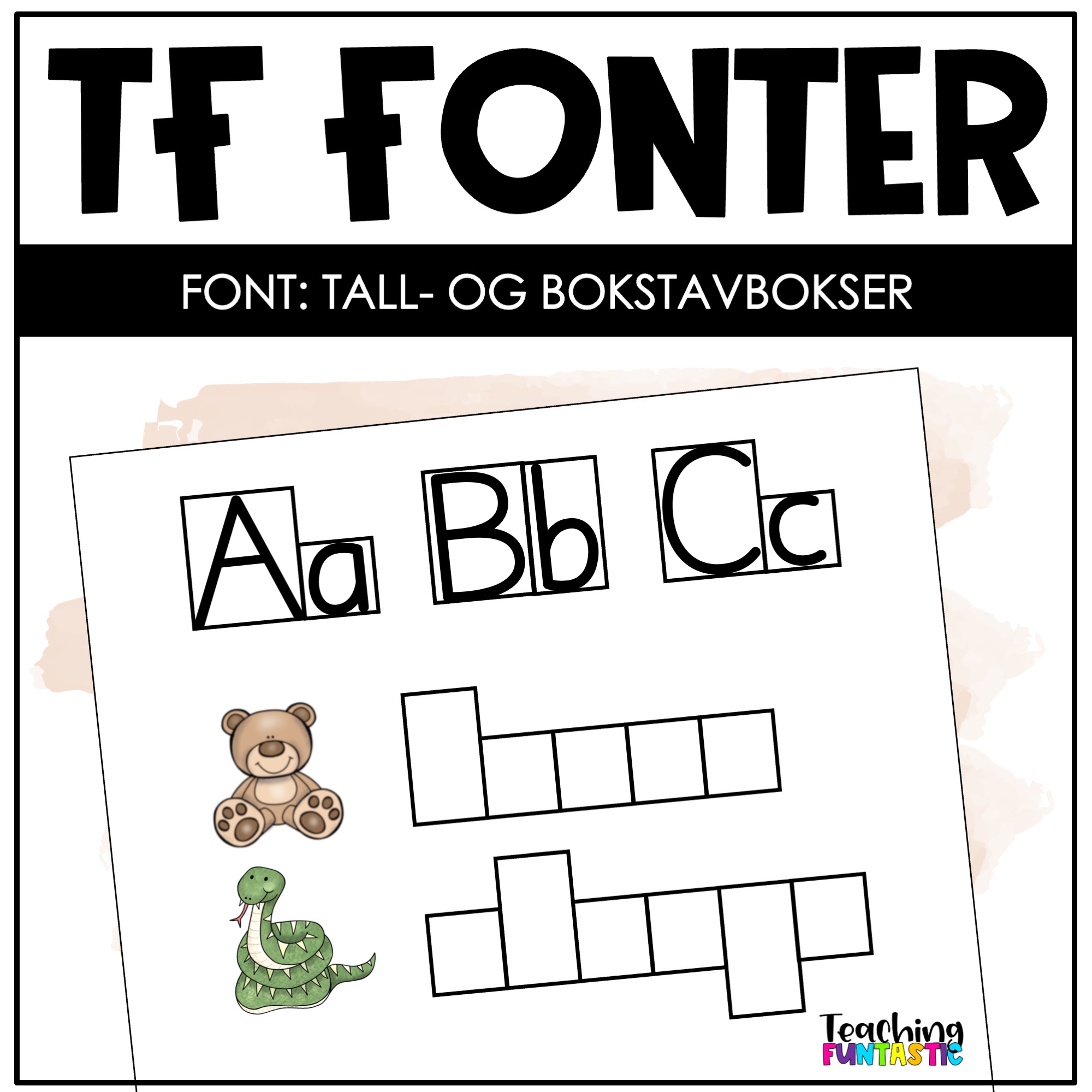
FUNtastic Tall- og bokstavbokser – font for staving og ordarbeid
FUNtastic Tall- og bokstavbokser er en smart font for lærere som vil lage egne oppgaver med bokstavbokser og stavetrening. Hver bokstav og tall får sin egen tydelige rute, slik at elevene kan se bokstavenes størrelse og plassering mens de øver på å stave ord.
Dette er en font for skole og undervisning som gjør det superenkelt å lage arbeidsark for skrivetrening, bokstavinnsetting og lydanalyse. Du skriver bare inn ordet du vil bruke, og fonten tegner automatisk bokstavbokser – klare til at elevene skal fylle inn riktige bokstaver.
Perfekt for staving og bokstavbevissthet
FUNtastic Tall- og bokstavbokser hjelper elevene å forstå hvordan bokstavene fyller ordets form og lydstruktur. Bokstavboksene gir visuell støtte i lydanalyse og staving, og passer perfekt for begynneropplæringen. Elevene får trene på å høre, se og skrive bokstaver i riktig rekkefølge – en viktig ferdighet i tidlig skriveutvikling. Fonten fungerer like godt til norsk, engelsk og spesialundervisning, der visuell støtte er ekstra nyttig.
Lag oppgaver raskt og enkelt